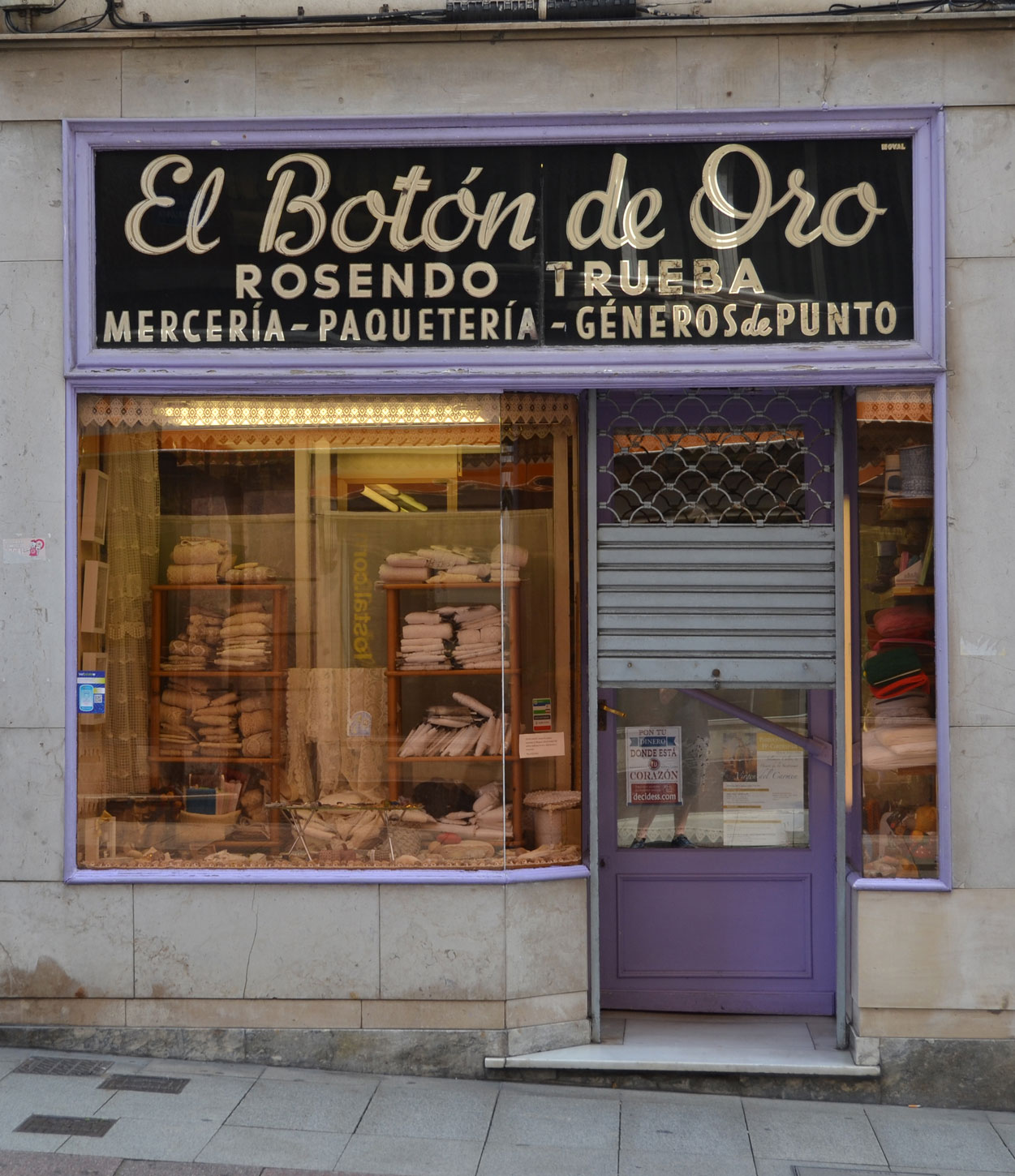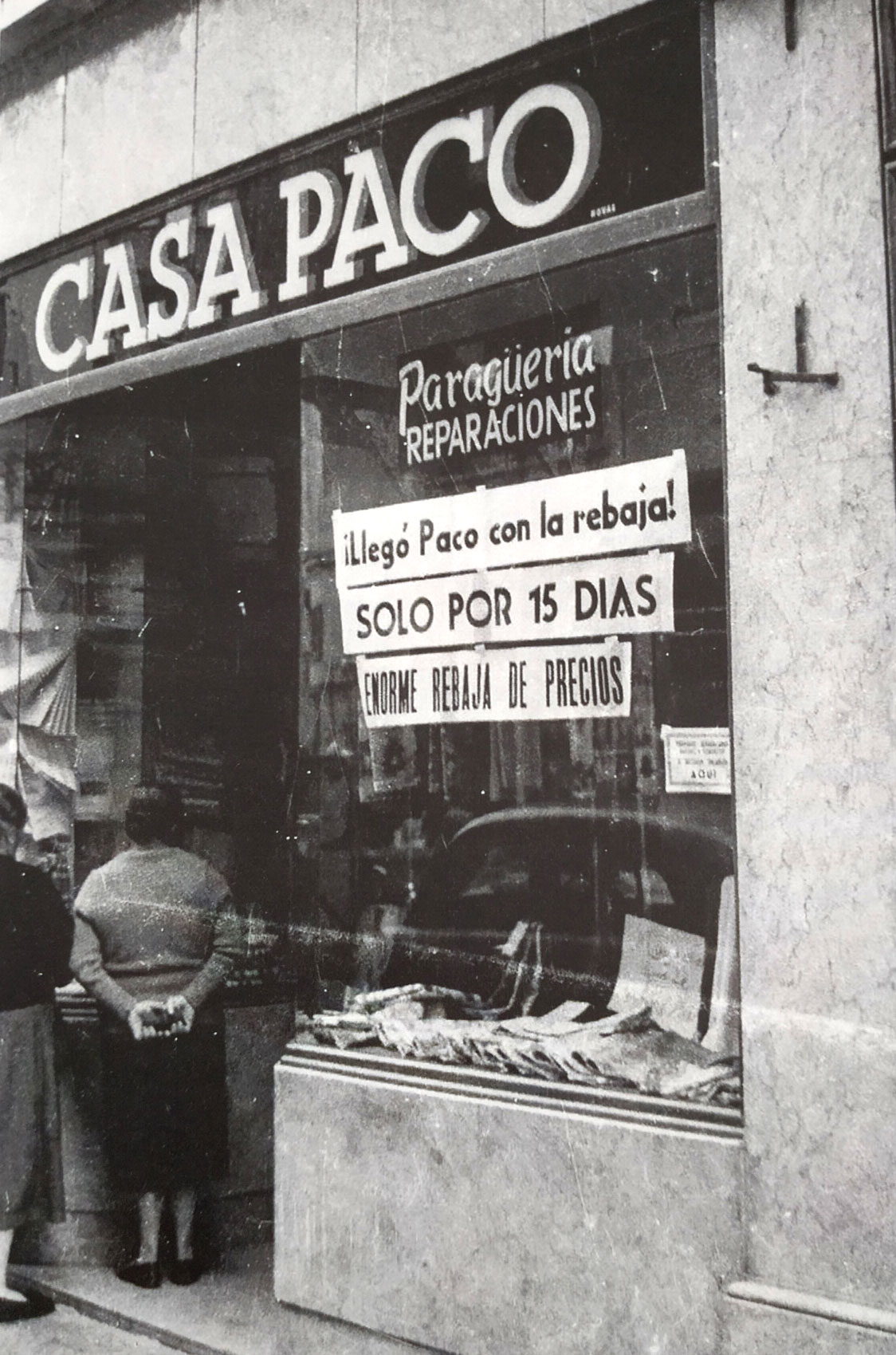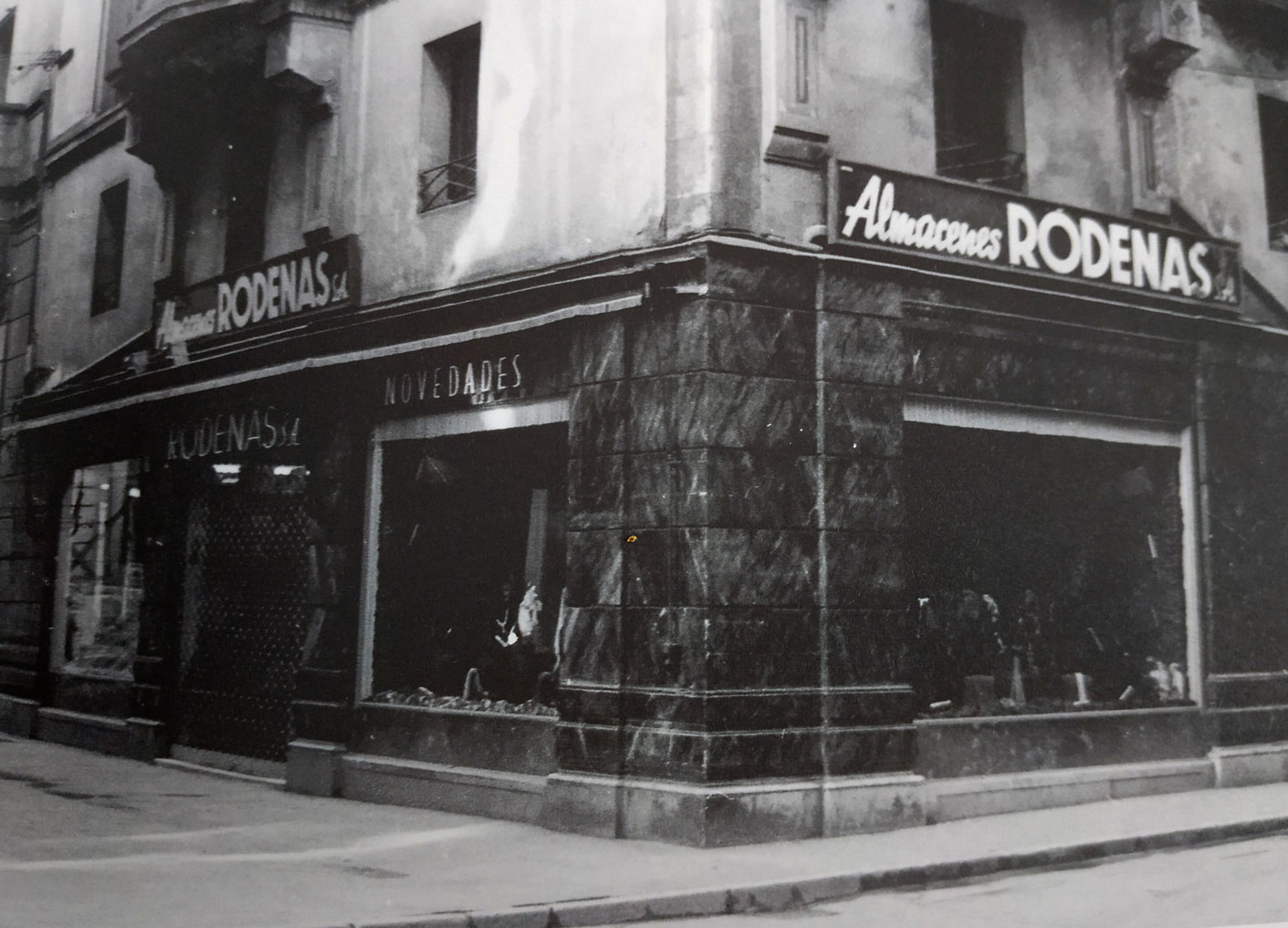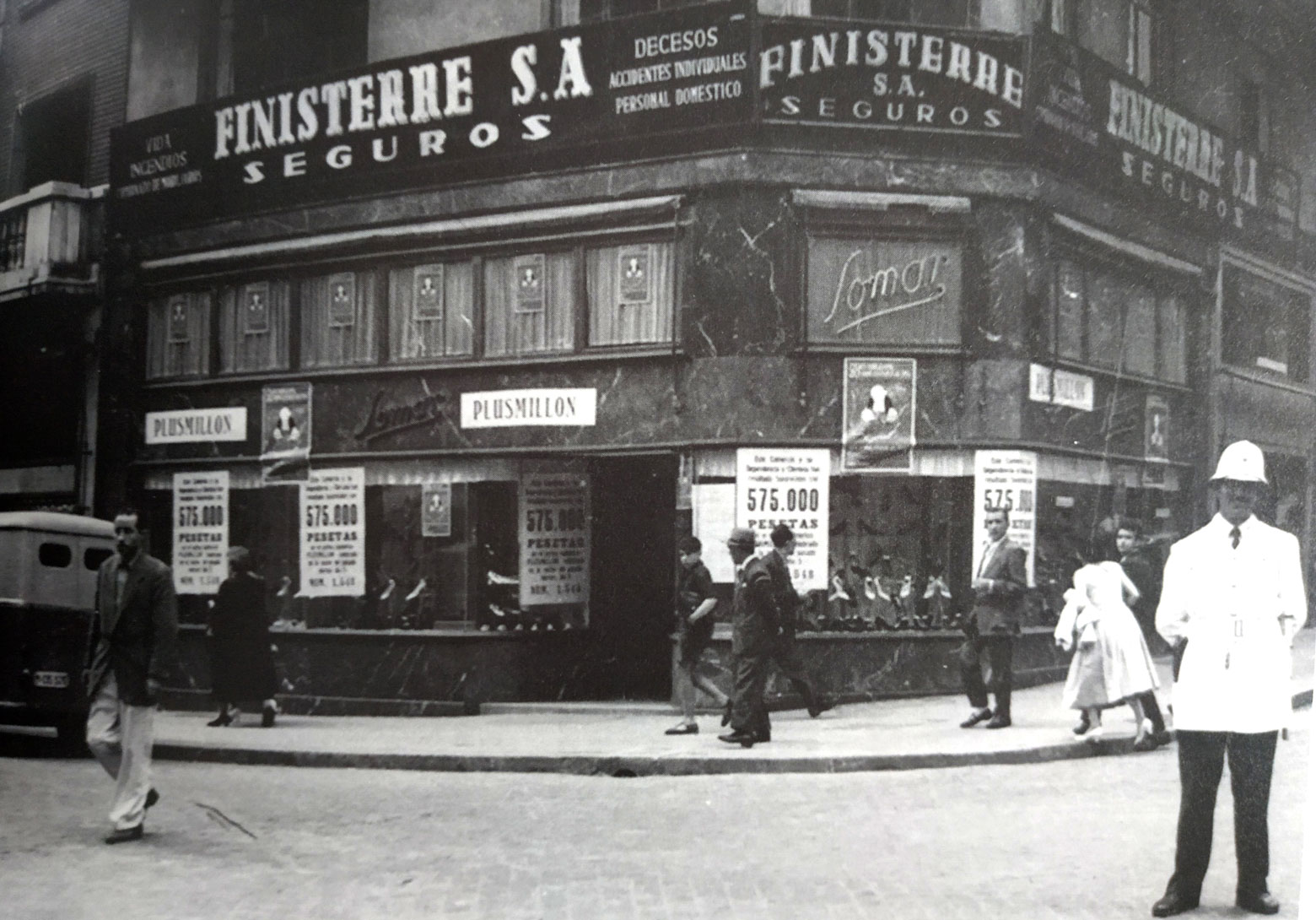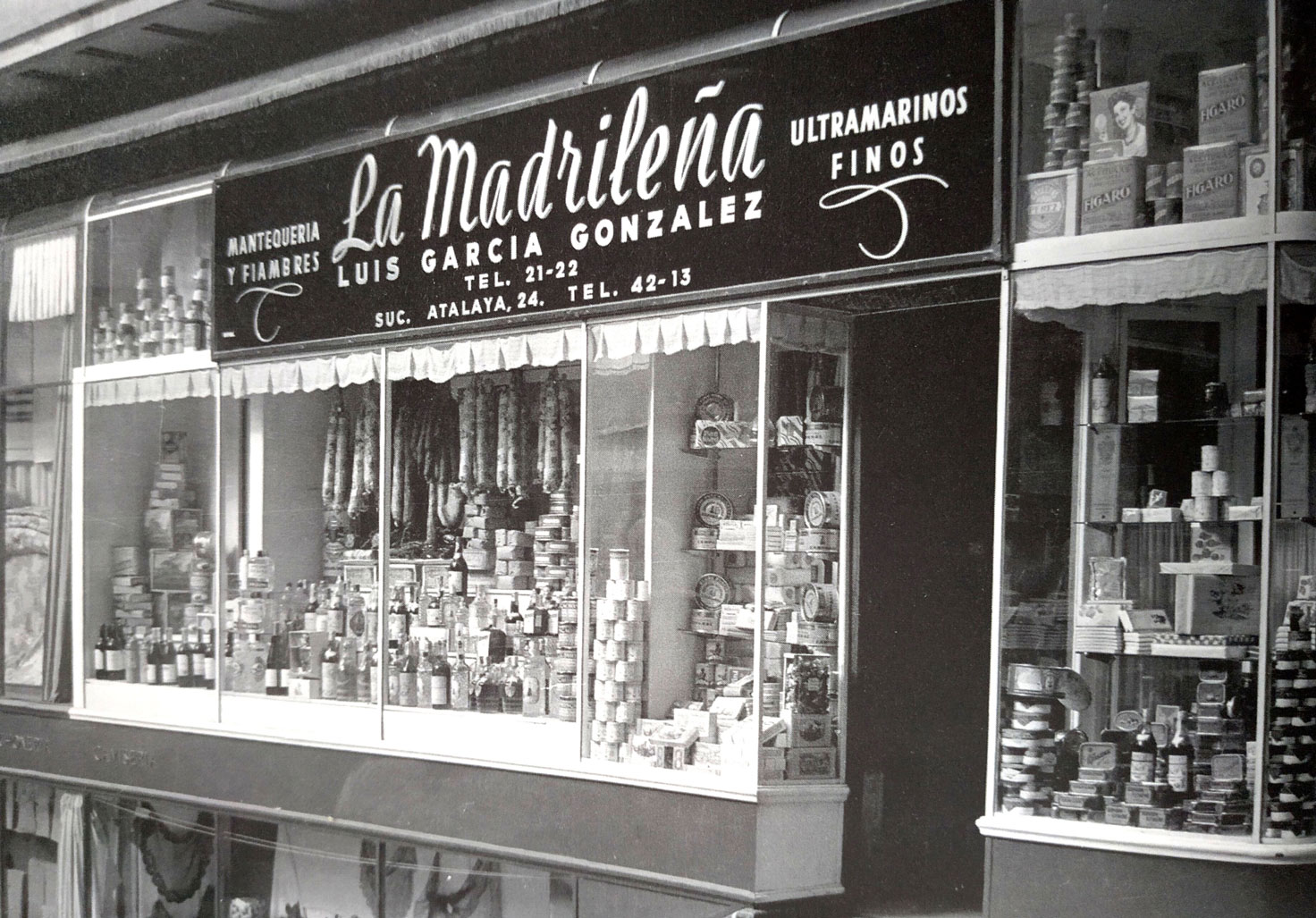
Rótulos de NOVAL
Hace un tiempo hablamos de la figura aparecida como Rotulista o Empresa de NOVAL a través de una firma en dos rótulos de Santander y Reinosa.
El Botón de Oro (Santander) foto: Santatipo
Mercería Ernesto (Reinosa). Foto: Santatipo
Sigo trabajando en buscar información de quien era. Mientras a través de alguna publicación he ido descubriendo a través de las fotos, algunos rótulos que ha realizado. Están identificados principalmente por la firma, aunque en algún detalle de la tipografía se puede ver la misma mano.
Casa Paco, calle Rualasal. Años 50. la firma está abajo a la de derecha de la O. Foto: Colección archivo privado Mazo (Extraída del libro «Vamos de tiendas» de César Pómbo) *La famosa frase de «que llega Paco con rebajas» proviene de aquí*
Bar El Solar. Ubicado en la calle Isabel II. Años 50. La firma está abajo a la derecha. El tipo de El Solar recuerda al «Botón de Oro». Foto: Colección archivo privado Mazo (Extraída del libro «Vamos de tiendas» de César Pómbo)
La Madrileña. info en Santatipo. Años 50. La firma está abajo a la izquierda (Foto: Colección archivo privado Mazo (Extraída del libro «Vamos de tiendas» de César Pómbo)
Almacenes Rodenas, en la Plaza del Príncipe. Años 50. La firma está arriba a la izquierda. Foto: Colección archivo privado Mazo (Extraída del libro «Vamos de tiendas» de César Pómbo)
Seguros Finisterre, en Juan de Herrera. Años 50. Aunque no se lee bien, parece que la firma está ubicada arriba a la derecha. Foto: Colección archivo privado Mazo (Extraída del libro «Vamos de tiendas» de César Pómbo).